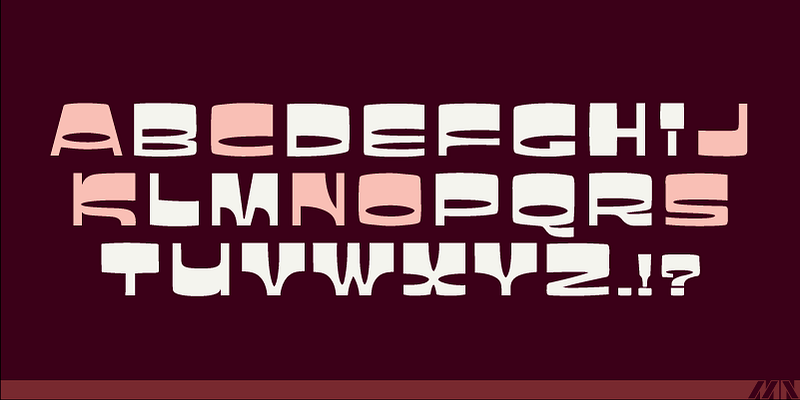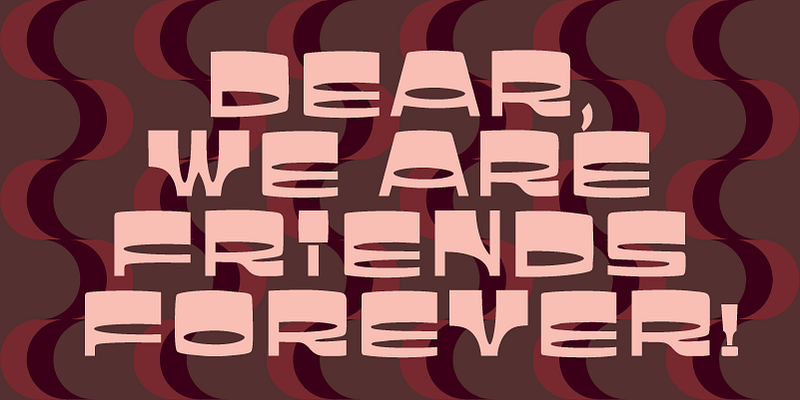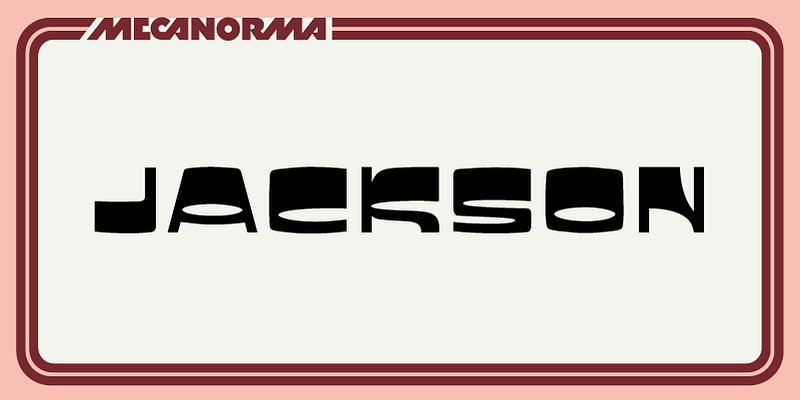
L’azienda francese Mecanorma era uno dei principali venditori mondiali di lettering a rub-down istantaneo. Nel 1995, Mecanorma si è ritirata dal mercato della grafica professionale. In quel periodo, i suoi prodotti di lettering a rub-down istantaneo erano realizzati da Trip Productions BV. Nel 2004, International TypeFounders (ITF) ha ottenuto la licenza per i caratteri digitali da Trip Productions BV e ha rilasciato il portfolio come Mecanorma Collection. Così facendo, ha preservato una delle migliori librerie di font digitali di caratteri da esposizione al mondo, combinando vere e proprie arti e mestieri negli strumenti di oggi. Nel 2014, ITF ha stipulato un accordo permanente con i successori di Trip Production. Questo accordo ha confermato i diritti digitali esclusivi mondiali di ITF sulla raccolta.